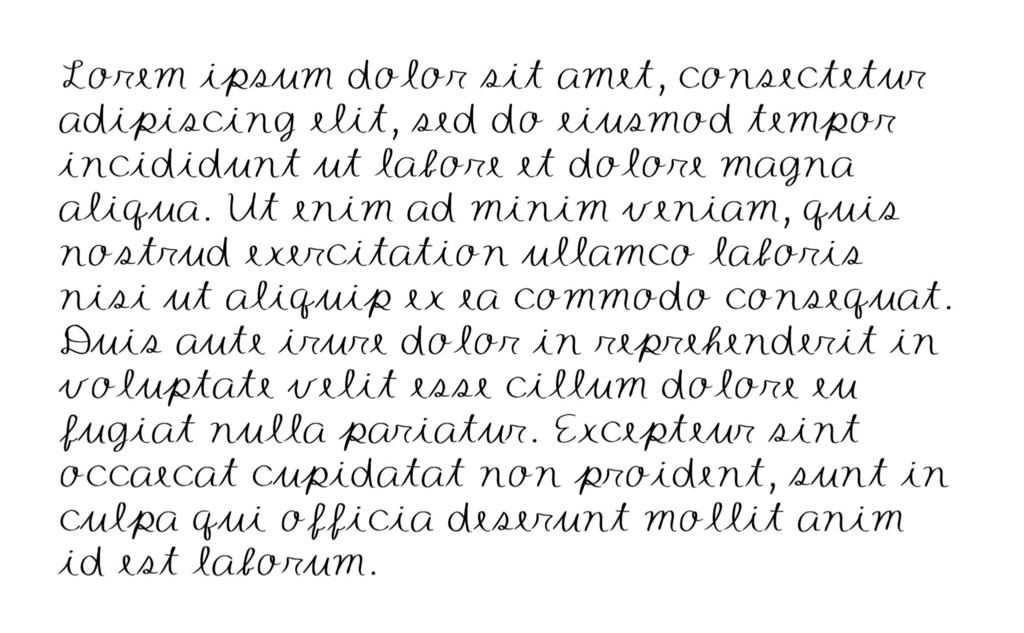
手書き風筆記体フォント
手書き風の筆記体フォントです。 一応繋がっているかと。 ・フォントデータを第三者に譲渡・配布・販売することはできません。 ・第三者に提供するような素材集や画像編集アプリ、webサービス等に作者への事前の許諾なしにフォントデータを組み込むことはできません。 ・公序良俗に反する目的、誹謗・中傷目的で使用することはできません。 ・フォントデータをサーバー上にアップロードすることはできません。 ・フォントを使用したロゴの商標登録はできません。 ・フォントのデータを元に、類似または同一フォントのデータを作成することはできません。 ・フォントデータの改変はできません。 ・フォントを使用して発生したと思われるいかなる問題についても、作者は責任を負わないものとします。